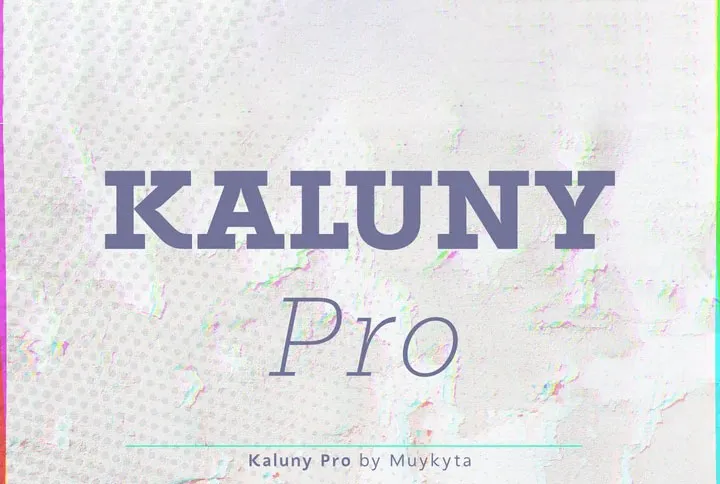
A Kaluny Pro Font Family é uma seleção de duas linhas que reúnem a modernidade com traços geométricos e os elementos clássicos para criar um impacto visual e emocional. Embora possa parecer uma fonte slab serif, na verdade possui dois versões: uma com traço e outra sem. Esta fonte é perfeitamente adaptada para uso em materiais que desejam destacar-se ao máximo, seja no design gráfico ou publicitário. Com sua combinação moderna de linhas finas e suaves, a Kaluny Pro oferece uma leitura fluida e uma estética uniforme dentro do mesmo conjunto. Isso torna-a ideal para aplicativos que buscam um equilíbrio entre seriedade clássica e o ar contemporâneo moderno de sua linhagem slab serif. Esta fonte é perfeita para anúncios, logos e materiais corporativos onde deseja-se transmitir uma mensagem moderna e atemporal em formato de letra.